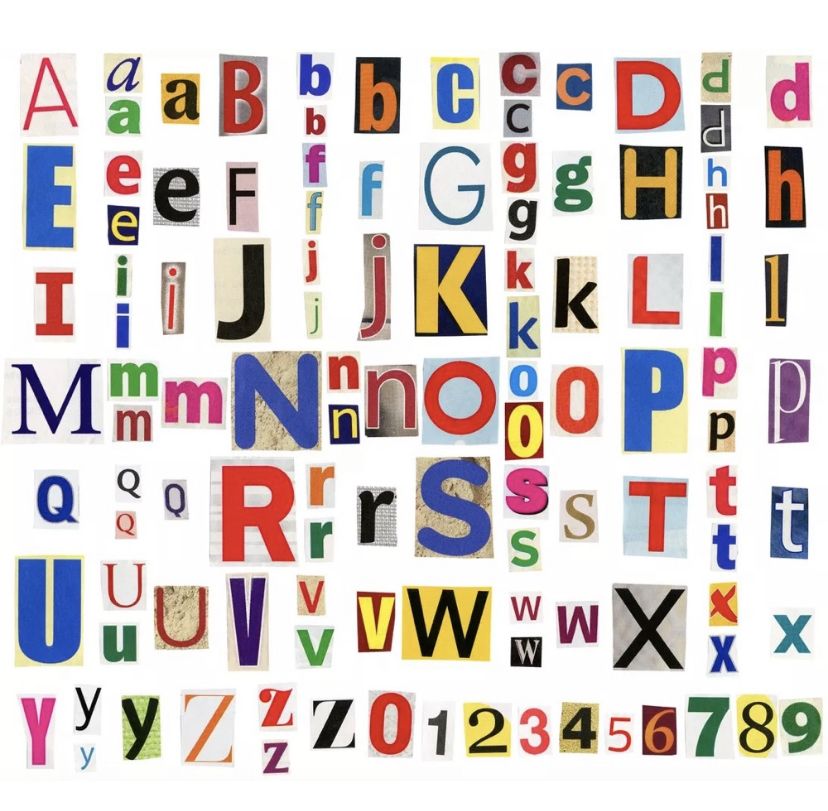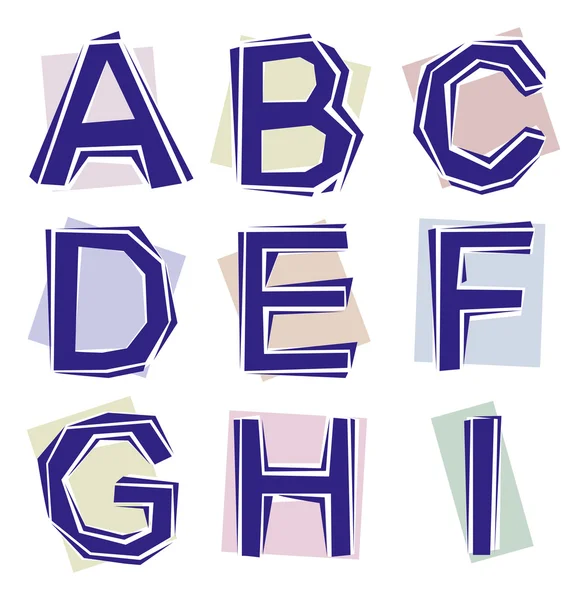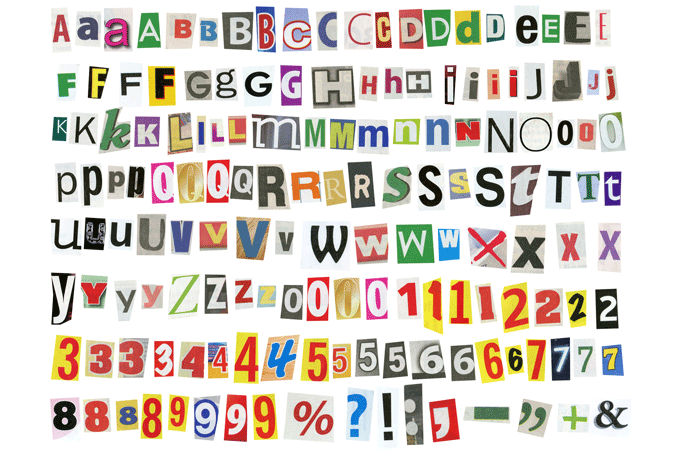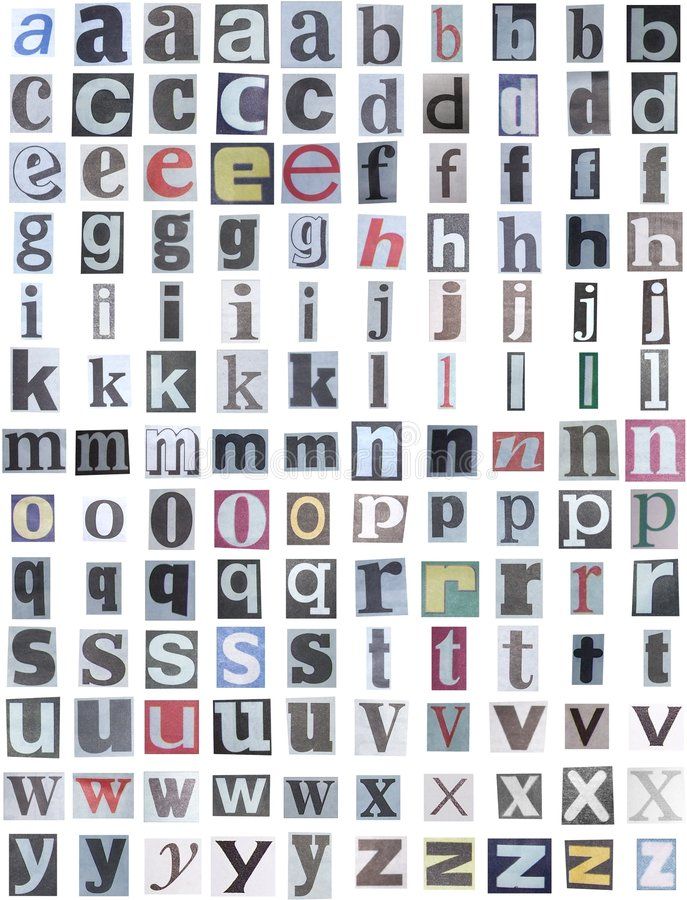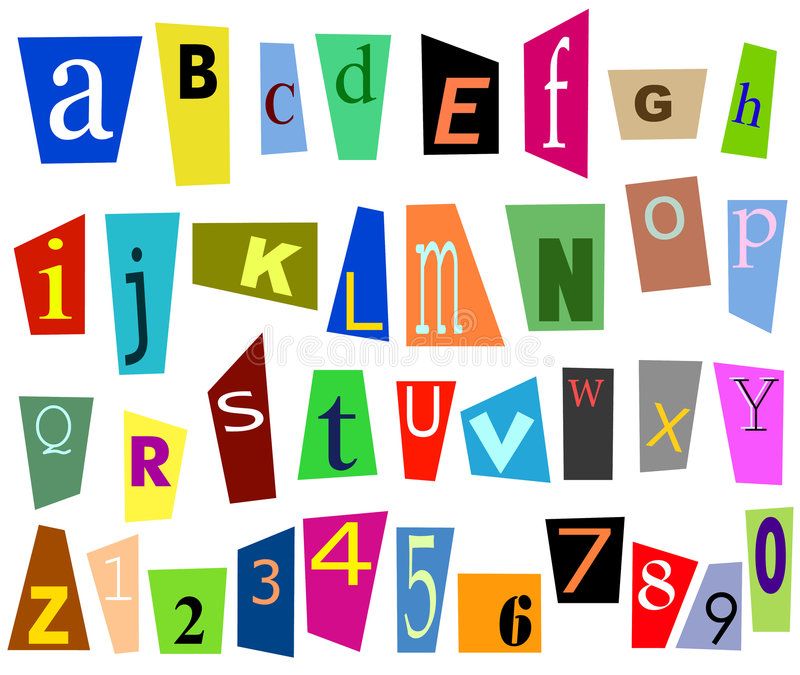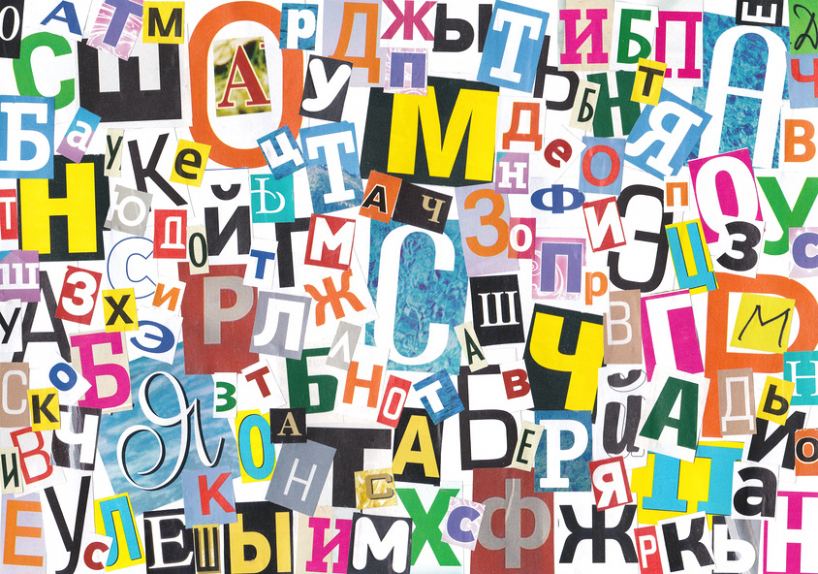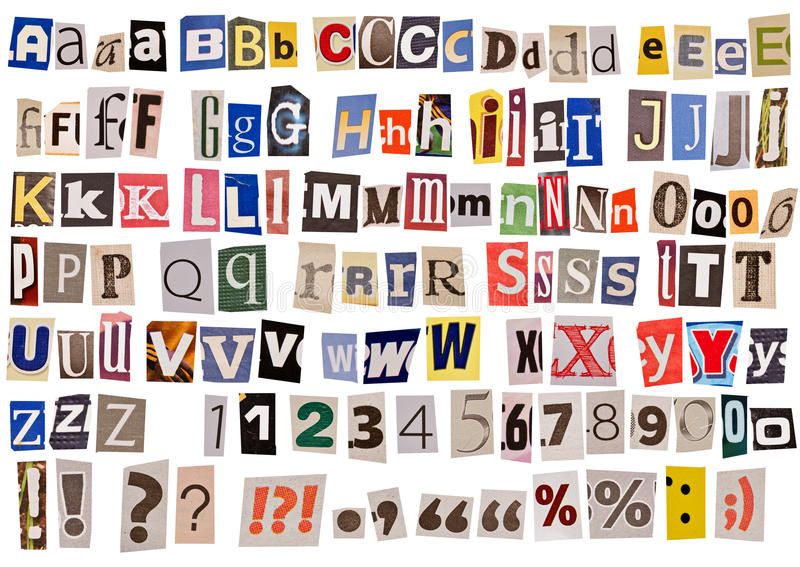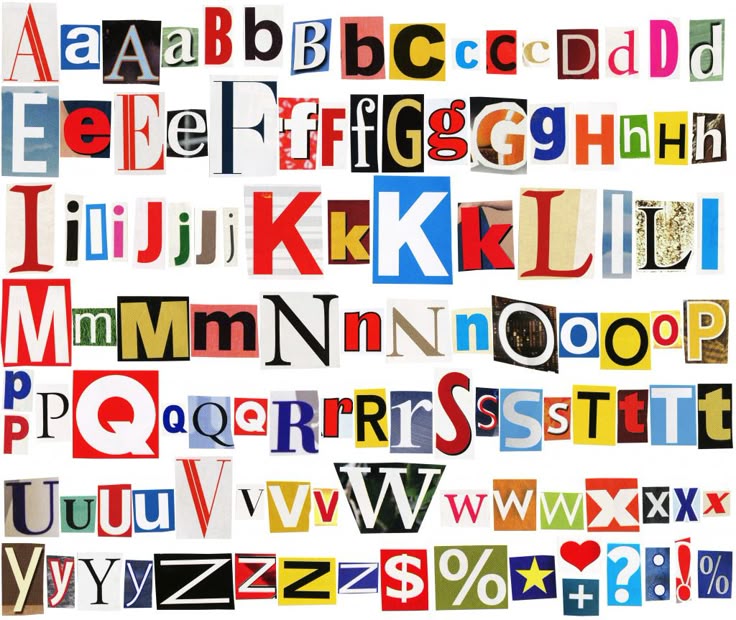
Несмотря на это, есть сторонние инструменты которые предлагают пользователям возможность размещать другие источники. Продолжайте с нами, чтобы узнать больше об этой альтернативе и узнать, как используйте шрифты, которые делают ваши публикации более привлекательными, в данном случае Cut Letter Generator.
Вырезать генератор букв. Если вам нужны дополнительные параметры для оформленного текста, просто нажмите «загрузить больше шрифтов». Варианты, которые появляются здесь, более случайны, немного отличаются от стандартных и смешивают ресурсы, у которых мало общего, смайлики и символы.
Отличие сайта в том, что на нем есть функция для создания самого шрифта. Щелкнув «Создай свой собственный шрифт», вы можете выбрать символы, которые будут соответствовать каждой букве алфавита.
Instagram и другие социальные сети создают шрифт, который лучше всего адаптируется к общему формату системы. Это часть единообразия, необходимого для визуального удобства просмотра этих платформ пользователями.
— Генератор вырезанных букв. Оказывается, есть способ добавить стилизованные буквы, которые на самом деле являются специальными символами, а также смайлики и другие символы. На практике они выглядят как пользовательские шрифты, но технически их называют Символы Юникода.
1. Откройте инструмент
Чтобы облегчить процесс, мы советуем вам использовать шрифты на том же устройстве, на котором вы получаете доступ к Instagram.
2. Напишите или вставьте свой текст
Второй шаг — написать или вставить в поле текст, в котором вы собираетесь применить настраиваемый шрифт.
Когда вы вводите или вставляете слова, появится список с вашим стилизованным фрагментом в разных шрифтах. Если вам нужно больше альтернатив, просто нажмите «загрузить больше шрифтов».